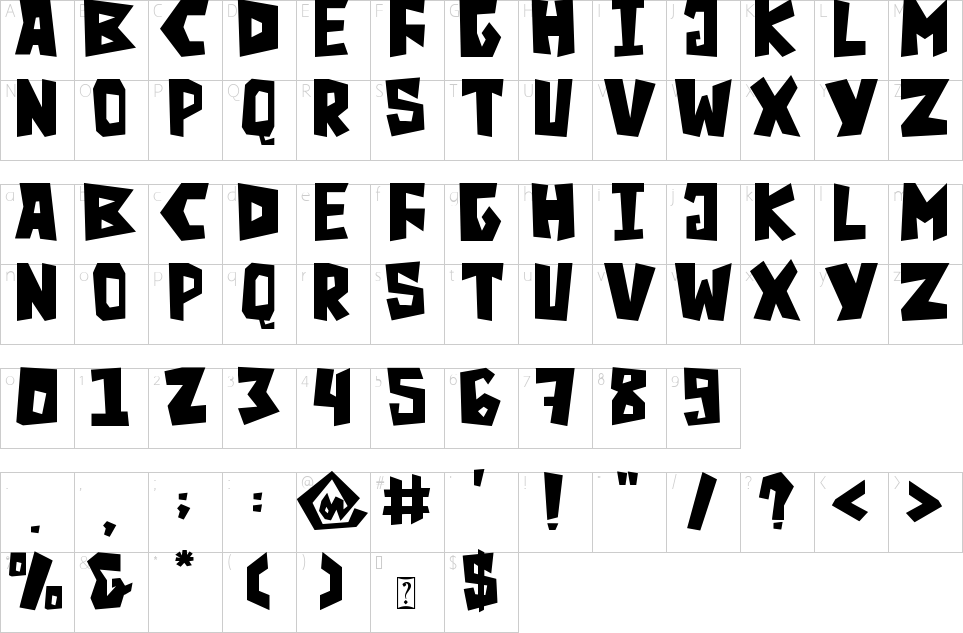
Descubra a beleza das Fontes Grátis com a Grufy, uma fonte exclusivamente disponível para download pela plataforma do ‘Grufy Font – 1001 Free Fonts’. Esta elegante e moderna fonte foi projetada por Stefani Tri Rosa Setiati Christiana. Com um design simples e sofisticado que se destaca em qualquer layout de texto, a Grufy é uma opção ideal para designers gráficos atentos ao detalhe. Seja você criando um site dinâmico ou prestando conteúdo em redes sociais, a Grufy pode transformar seu design sem deixar sair da sua mão. Não perca tempo, colecione essa fonte e seja o primeiro a experimentá-la para criar algo único. Mais de 1.970 pessoas já tiveram a oportunidade de usar esta fonte, então você não quer perder esta chance também? Download agora para explorar e experimentar a beleza da Grufy.